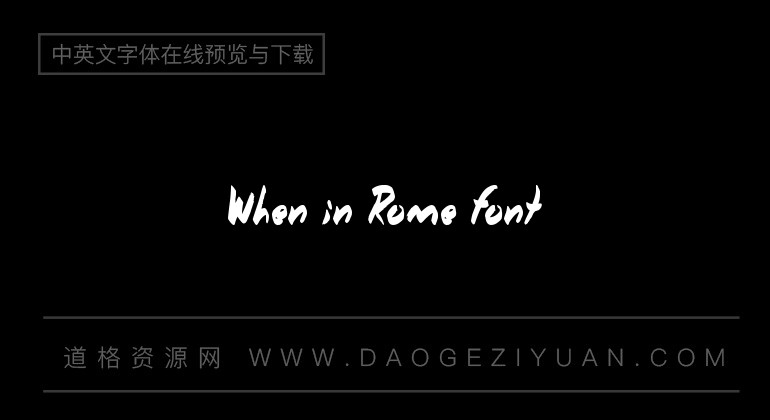
"When in Rome"是一种字体,它的设计受到了古罗马时期的影响,因此它的字体形状和设计风格都具有古老的感觉。该字体是由Hannes Siengalewicz在2010年创建的,可用于许多不同类型的设计项目,包括海报、标志、包装等等。它具有粗犷、坚定和强大的外观,适合用于需要突出显示内容的场合。"When in Rome"字体的使用范围很广,尤其适合设计师在需要表现古老、耐久和具有权威性的设计时使用。内容介绍
When in Rome Font是一款非常不错的手写艺术字体,具有很好的视觉感,适合于文化类的宣传设计、商业类品牌的广告和产品包装设计以及个性化文字排版等较多场景。